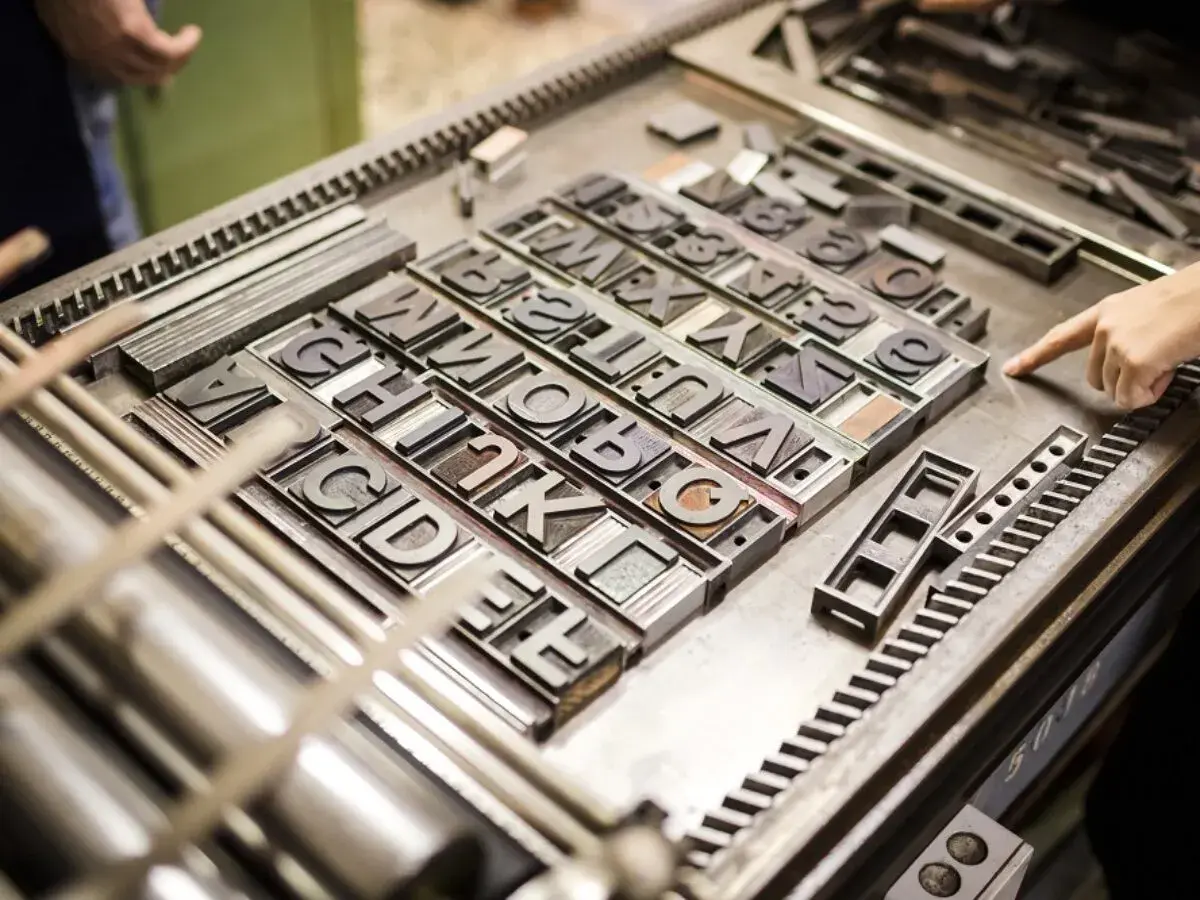
Najważniejsze różnice i praktyczne wnioski dla codziennej pracy z typografią
- Font to cyfrowa postać kroju pisma, czyli plik lub zestaw plików używanych w komputerze.
- Czcionka to historycznie metalowy nośnik znaków; w mowie potocznej bywa używana szerzej, ale fachowo nie oznacza tego samego co font.
- Krój pisma opisuje wygląd liter, a nie sam plik techniczny.
- W reklamie lokalnej liczy się przede wszystkim czytelność, spójność i dopasowanie do charakteru marki.
- Najczęstsze błędy to zbyt wiele krojów, za mały kontrast i dekoracyjność, która psuje odbiór tekstu.
Najkrótsze rozróżnienie między fontem, czcionką i krojem pisma
Jeżeli chcę wyjaśnić ten temat bez żargonu, zaczynam od prostego porządku. Krój pisma to wygląd liter, font to jego cyfrowa postać, a czcionka ma znaczenie historyczne i odnosi się do dawnego nośnika znaków używanego w druku. W praktyce wiele osób używa tych słów zamiennie, ale jeśli zależy Ci na precyzji, warto trzymać się tego rozróżnienia.
| Pojęcie | Co oznacza | Jak myśleć o tym w praktyce |
|---|---|---|
| pismo | System znaków używany do zapisu mowy i myśli | Najszersza kategoria, pod którą mieszczą się litery, cyfry i znaki |
| krój pisma | Zaprojektowany wygląd znaków, np. geometryczny, humanistyczny, szeryfowy | To właśnie o krój najczęściej pytasz, gdy oceniasz styl liter |
| font | Cyfrowy plik lub zestaw plików z konkretnym krojem pisma | To, co instalujesz, pobierasz lub osadzasz w projekcie |
| czcionka | Historyczny nośnik znaków w druku | Fachowo to nie to samo co font, choć potocznie bywa używana szerzej |
Warto jeszcze dopowiedzieć jedną rzecz: glif to konkretny kształt znaku, czyli to, jak wygląda litera, cyfra albo znak interpunkcyjny w danym kroju. Dzięki temu łatwiej zrozumieć, dlaczego dwa fonty mogą wyglądać podobnie, ale mieć inną konstrukcję, wagę lub rytm światła między znakami. To właśnie na tym poziomie zaczyna się prawdziwa typografia, a nie na samym wyborze „ładnych literek”.
Dlaczego to rozróżnienie ma znaczenie w reklamie lokalnej
W projektach dla małych firm typografia nie jest ozdobą na końcu procesu. Ona wpływa na to, czy marka wygląda profesjonalnie, czy amatorsko, czy tekst da się przeczytać z ulicy, i czy klient zaufa komunikatowi w kilka sekund. Dla lokalnego biznesu to bywa ważniejsze niż najbardziej efektowna paleta kolorów.
Najczęściej widzę trzy sytuacje, w których precyzyjne myślenie o kroju ma realny wpływ na wynik:
- Strona internetowa - zbyt dekoracyjny font potrafi obniżyć czytelność oferty i utrudnić szybkie podjęcie decyzji.
- Materiały drukowane - ulotka, wizytówka albo menu musi dać się odczytać bez wysiłku, bo klient nie poświęca na nie dużo czasu.
- Szyld i oznakowanie - jeśli litery są zbyt cienkie, ciasne albo fantazyjne, marka traci widoczność z większej odległości.
Ja w takich projektach patrzę najpierw nie na „oryginalność”, tylko na czytelność, charakter i spójność. Dopiero potem pytam, czy krój ma być nowoczesny, elegancki, przyjazny czy bardziej techniczny. To prostsza kolejność niż udawanie, że typografia jest decyzją wyłącznie estetyczną. Z tego miejsca łatwo przejść do praktyki: jak dobierać fonty do konkretnego kanału komunikacji.
Jak dobierać krój do strony, druku i szyldu
Dobrze dobrany krój pisma działa trochę jak ton głosu marki. Może być spokojny, pewny siebie, energiczny albo miękki, ale przede wszystkim musi pasować do sytuacji. Inny zestaw znaków sprawdzi się na stronie usługowej, inny w katalogu, a jeszcze inny na wielkim banerze przed lokalem.
Na stronie internetowej
W internecie najbezpieczniej działają kroje proste, dobrze renderujące się na ekranach i czytelne także na telefonie. W praktyce często wystarcza jedna rodzina fontów z kilkoma wagami, na przykład regular, medium i bold. Dla tekstu podstawowego zaczynam zwykle od 16-18 px, a linię ustawiam w okolicach 1.5-1.7, bo to daje komfort czytania przy dłuższych akapitach.Jeśli strona ma charakter usługowy, lepiej sprawdzają się kroje bezszeryfowe. Jeśli marka chce wyglądać bardziej premium, można sięgnąć po szeryf, ale pod warunkiem, że nie traci czytelności na małym ekranie. Na landing page dla lokalnej firmy najważniejsza jest szybkość skanowania treści, nie pokaz typograficzny.
W druku
W materiałach drukowanych można pozwolić sobie na odrobinę więcej charakteru, ale tylko wtedy, gdy nie cierpi na tym czytelność. Tekst podstawowy w ulotkach zwykle mieści się w zakresie 9-11 pt, a nagłówki mogą być wyraźnie większe, często od 18 pt wzwyż. Przy małych formatach szczególnie pilnuję kontrastu między tytułem a akapitem, bo bez tego projekt wygląda płasko i męczy wzrok.
Warto też pamiętać, że cienkie odmiany kroju mogą w druku wypaść słabiej niż na ekranie. To jeden z tych detali, które wyglądają dobrze w podglądzie, a gorzej po wydruku próbki. Dlatego zawsze testuję choćby prosty proof, zanim zaakceptuję finalny plik.
Na szyldzie i w przestrzeni
Przy szyldach i oznakowaniu kieruję się zasadą minimalizmu. Im dalej odbiorca stoi, tym prostszy powinien być krój i tym większa musi być odległość między literami oraz sam rozmiar znaków. Ozdobne skrypty, bardzo wąskie litery i przesadnie delikatne szeryfy są tu ryzykowne, bo zanikają w ruchu i w gorszym świetle.
W lokalnym marketingu wygrywa typografia prosta, czytelna i spójna z charakterem marki. Jeśli chcesz z tego wyciągnąć jedną regułę na przyszłość, niech będzie ona taka: najpierw czytelność i zastosowanie, dopiero potem efekt. To podejście działa przy stronie internetowej, szyldzie, ulotce i grafice do social mediów, a przy okazji oszczędza wielu rozczarowań po drodze.